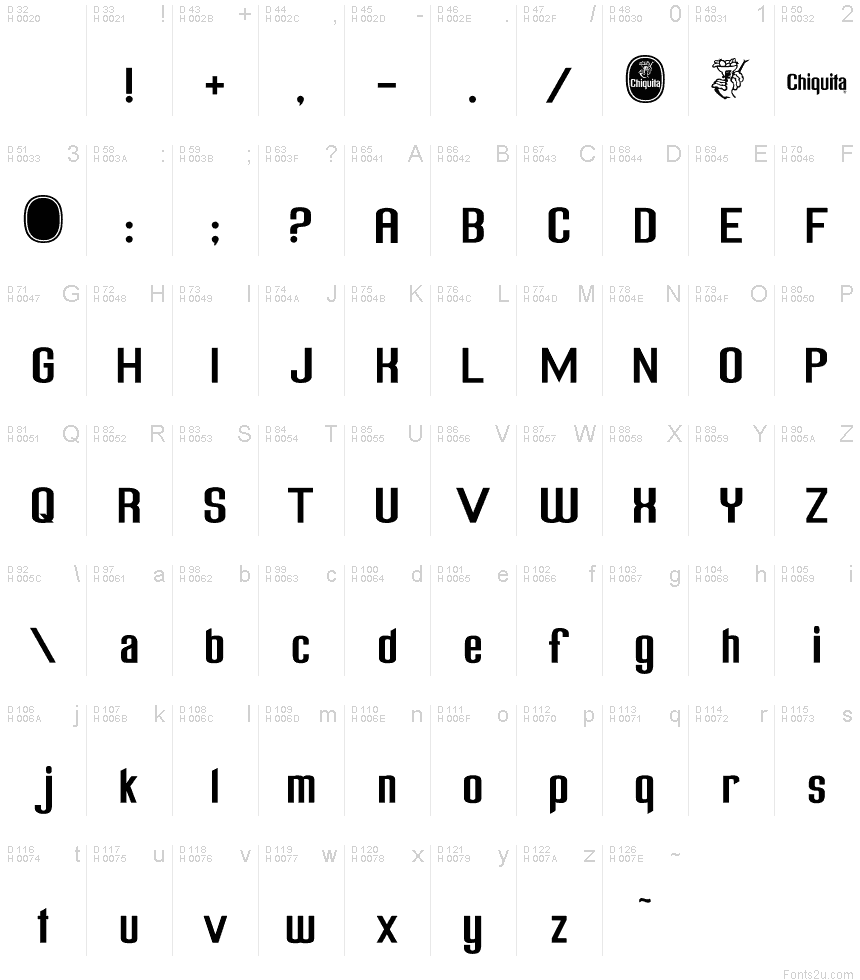
Chiquita di Samuel Park è un font gratuito sans serif condensato, dal carattere audace e perfetto per i poster. I tratti verticali decisi, la spaziatura stretta e gli angoli leggermente arrotondati gli conferiscono un aspetto denso e "inchiostrato", che ricorda quasi un timbro sulla pagina. Queste lettere sottili e slanciate creano un ritmo forte, rendendo anche una parola breve un blocco grafico pronto da inserire nel layout.
Con Chiquita, i tuoi titoli acquisiranno subito un tocco retro di grande impatto, ideale per locandine di concerti, fanzine, packaging, loghi, copertine editoriali e grafiche audaci per i social. Questo font gratuito dà il meglio di sé in grande formato, dove le sue forme compresse possono essere sovrapposte per creare composizioni dramatiche. Prova ad abbinare Chiquita a un font sans serif geometrico pulito o a un grottesco leggero per il testo principale, così da mantenere il focus sulla sua energia verticale e massiccia.